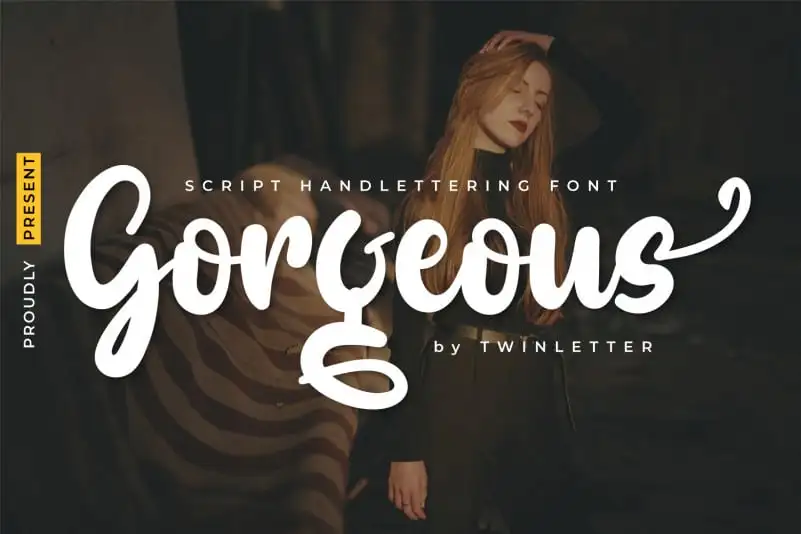
Gorgeous Script Font – Fonte Grátis
Gorgeous Script Font
A Gorgeous Script Font é uma nova criação do designer twinletter, revolucionária para quem busca elegância e sofisticação no seu design visual. Ela se destaca por suas delicadas traçadas artesanais que deslizam suavemente sobre a tela, intercalando linhas suaves com curvas dramáticas e arredondadas sutis. Esta fonte oferece uma atmosfera envolvente, ideal para aplicações em anúncios de marcas, logotipos ou qualquer projeto que deseje destacar-se com estilo e elegância. Com sua fidelidade a traçados artesanais, esta Gorgeous Script Font é perfeita para criar um texto com textura, tornando o seu design visualmente atraente e único.